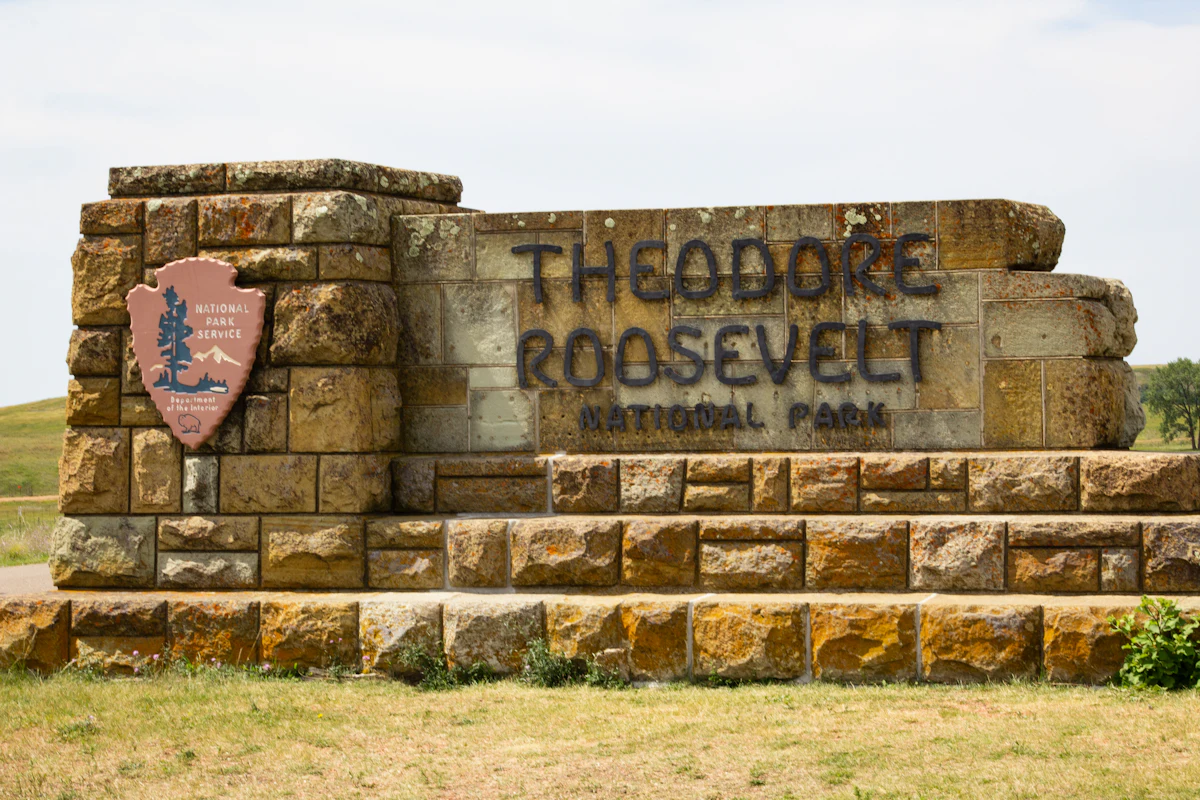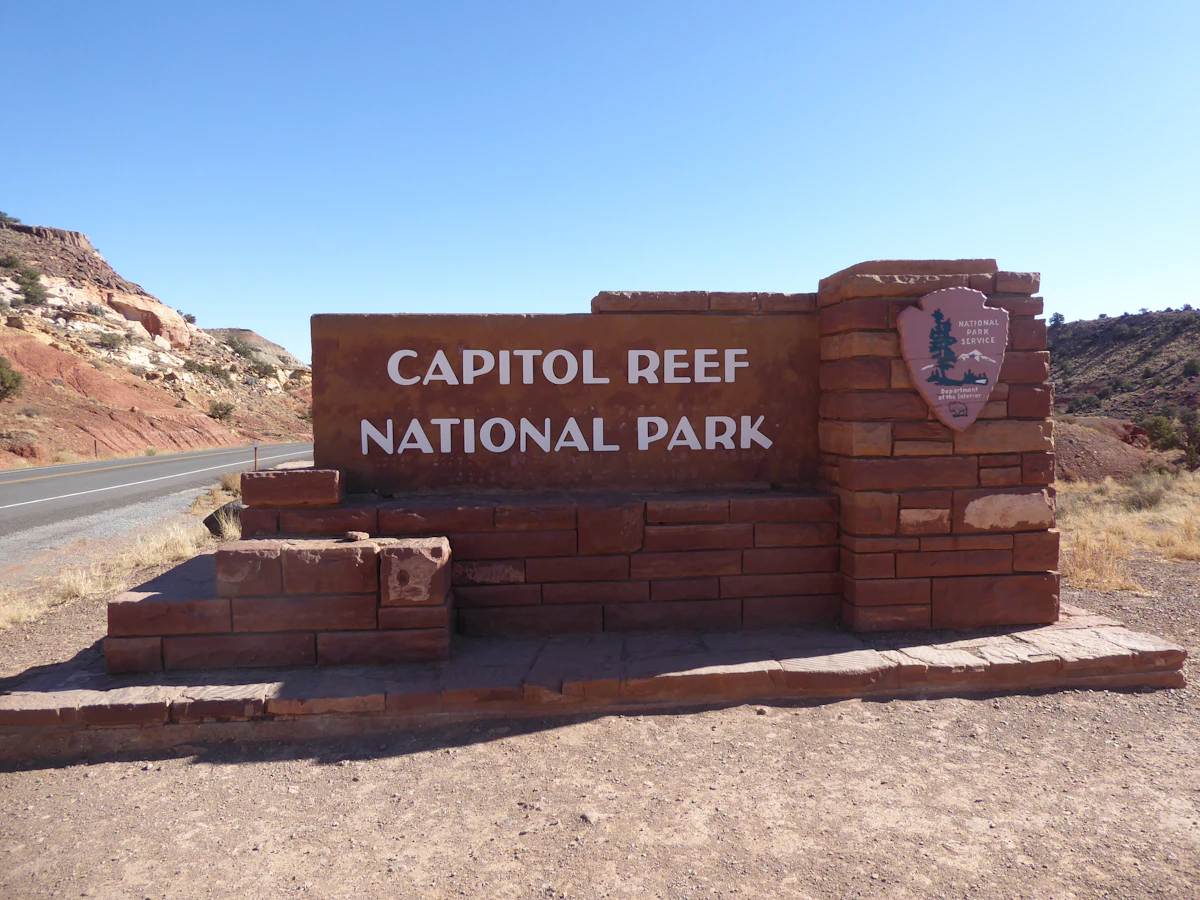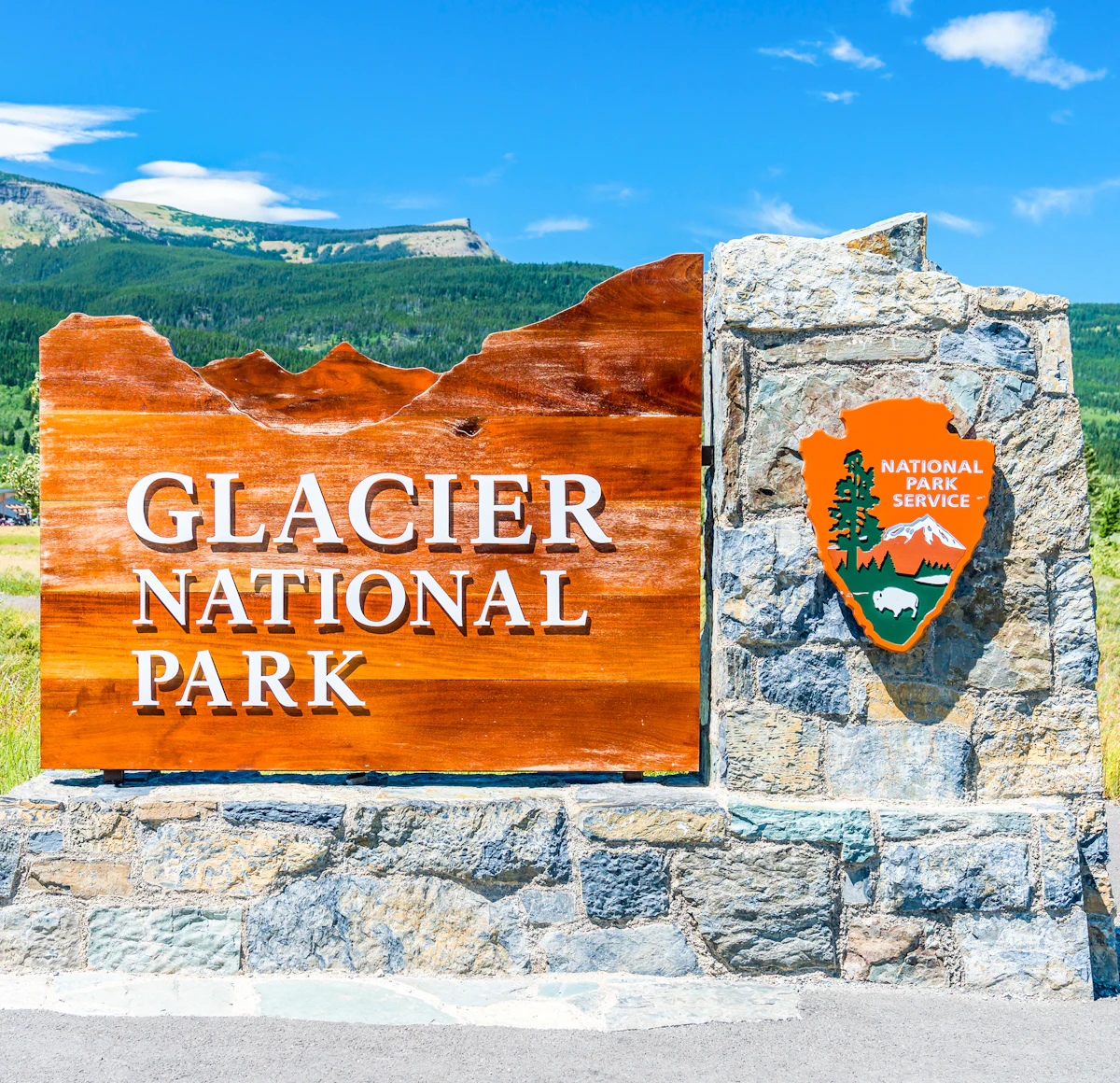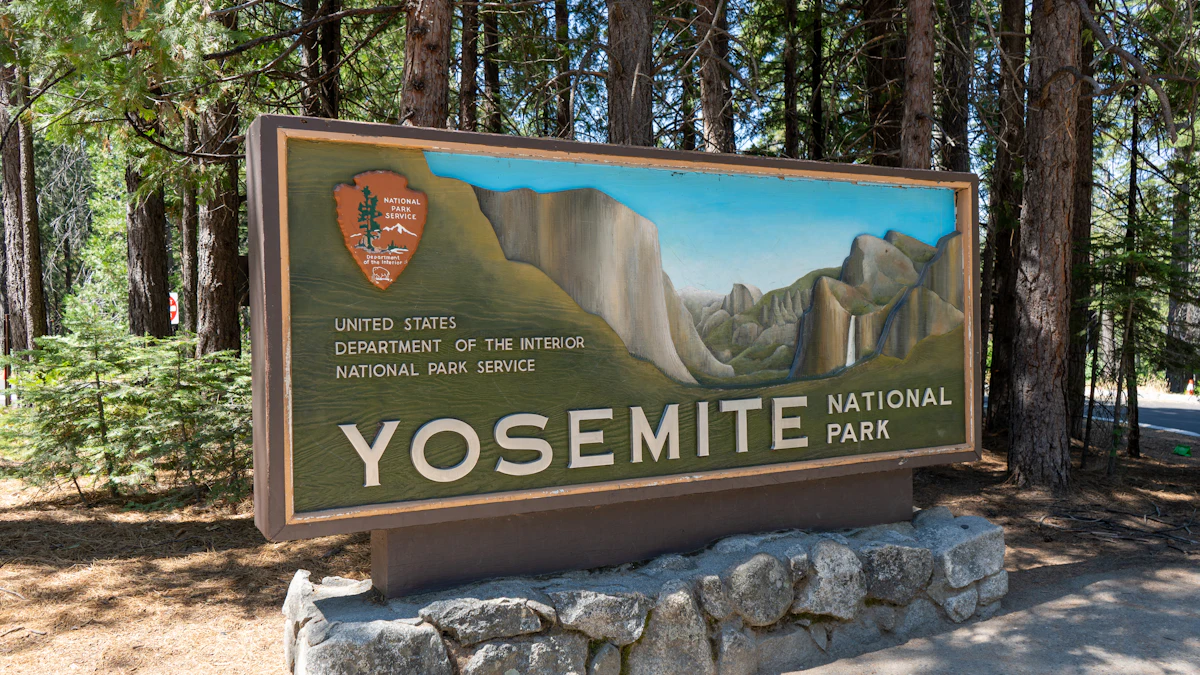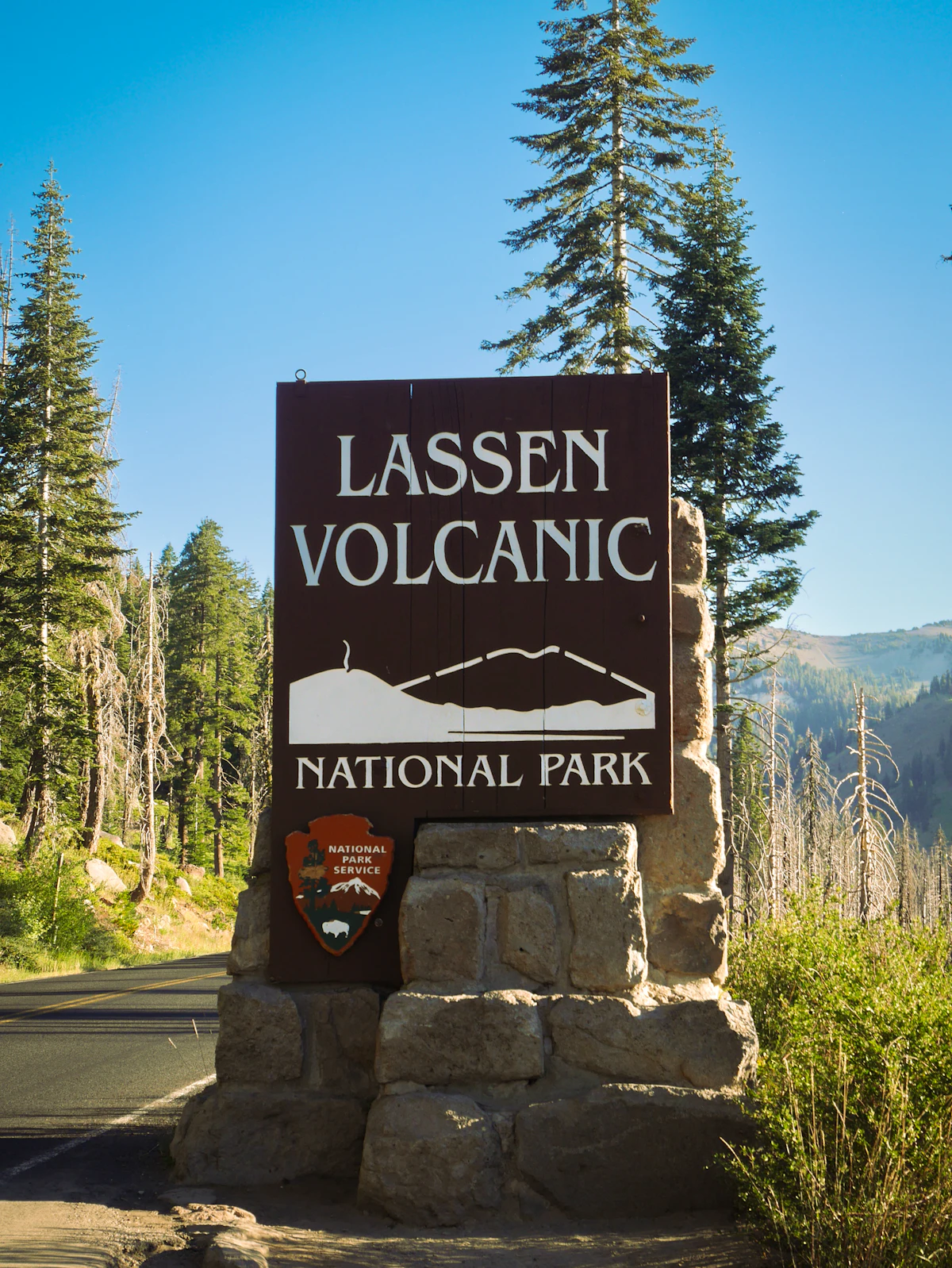
ที่ทางเข้าอุทยานแห่งชาติในอเมริกา ก่อนจะได้เห็นภูเขาหรือผืนป่า สิ่งแรกที่รถทุกคันขับผ่านคือป้ายหินหรือไม้สีน้ำตาลเข้ม บนนั้นมีชื่ออุทยานเป็นตัวอักษรหนาหนัก ปลายเส้นแต่ละขีดมีเชิงเล็กๆ โค้งรับกับเส้นตั้งอย่างพอดี หลายคนขับผ่านมันนับครั้งไม่ถ้วนโดยไม่เคยรู้ว่าตัวอักษรนั้นมีชื่อ มันคือ Clarendon
ฟอนต์ Clarendon ไม่ได้ถือกำเนิดมาเพื่อธรรมชาติหรือผืนป่าเลย มันเกิดกลางเมืองลอนดอนในปี 1845 ห่างจากอุทยานอเมริกาทั้งในแง่เวลาและสถานที่ คนออกแบบคือ Robert Besley แห่งโรงหล่อตัวพิมพ์ Fann Street Foundry
ชื่อ Clarendon มาจากสำนักพิมพ์ Clarendon Press แห่งออกซ์ฟอร์ด สิ่งที่ทำให้มันถูกจดจำในประวัติศาสตร์ตัวพิมพ์คือ Besley จดทะเบียนแบบตัวอักษรนี้ภายใต้กฎหมาย Ornamental Designs Act ทำให้ Clarendon กลายเป็นฟอนต์ตัวแรกของโลกที่ถูกจดทะเบียนคุ้มครอง ทว่าการคุ้มครองอยู่ได้เพียงสามปี พอหมดอายุ โรงหล่ออื่นก็แห่กันลอกแบบไปทันที
ป้ายทางเข้า Glacier National Park ตัวอักษร Clarendon บนแผ่นไม้
ในแง่รูปทรง Clarendon เป็นสแลบเซอริฟ คือมีเชิงตัวอักษรหนาเป็นแท่ง แต่ Besley ทำให้มันนุ่มลงด้วยการใส่เชิงโค้งตรงมุมที่เส้นตั้งบรรจบกับเชิง น้ำหนักของมันอยู่กึ่งกลางระหว่างตัวพิมพ์อียิปเชียนที่หนาทึบกับโรมันที่บางเบา เดิมทีมันถูกออกแบบมาเพื่อเป็นตัวเน้น วางคู่กับเนื้อความปกติในพจนานุกรมหรือหนังสือ เพื่อให้คำสำคัญเด่นขึ้นมาโดยไม่ต้องใช้ฟอนต์อื่น
ป้าย Yosemite National Park แกะสลักด้วยฟอนต์ Clarendon
ไม่นานหลังเกิดขึ้น Clarendon ก็ข้ามมหาสมุทรไปอเมริกา ช่วงทศวรรษ 1850 โรงงานเริ่มผลิตมันเป็นตัวพิมพ์ไม้ขนาดใหญ่ มันกลายเป็นเสียงของสิ่งพิมพ์อเมริกันที่ต้องการความหนักแน่น พาดหัวข่าวหนังสือพิมพ์ โปสเตอร์โฆษณา และโปสเตอร์ประกาศจับคนร้ายยุคตะวันตก ล้วนใช้ตัวอักษรหนาแบบนี้ในการตะโกนข้อความออกมา
ป้าย Capitol Reef National Park ตัวอักษร Clarendon สีขาวบนหินแดง
หลายสิบปีต่อมา Clarendon เดินทางมาถึงงานที่ทำให้มันเป็นที่จดจำที่สุดในสายตาคนทั่วไป นั่นคือป้ายของ National Park Service ระบบป้ายสีน้ำตาลที่กระจายอยู่ทั่วอุทยานเลือกใช้ Clarendon เป็นตัวอักษรหลัก เพราะมันให้ความรู้สึกแข็งแรงทนทานแต่ยังอบอุ่นเป็นมิตร อ่านง่ายแม้มองจากรถที่กำลังแล่น เชิงหนาๆ ของมันยังคงคมชัดแม้ถูกแกะสลักลงบนไม้หรือหิน
ป้าย Lassen Volcanic National Park ฟอนต์ Clarendon บนแท่นหิน
มีบางอย่างชวนคิดในเส้นทางของตัวอักษรชุดนี้ ฟอนต์ที่ถูกสร้างมาเพื่อเน้นคำในหนังสือ กลับลงเอยด้วยการเป็นเสียงพูดแทนผืนป่า ตัวอักษรหน้าตาเดียวกับที่เคยตะโกนคำว่า WANTED บนโปสเตอร์ ทุกวันนี้กลับทำหน้าที่บอกให้คนชะลอความเร็วและก้าวเข้าหาความเงียบ เช่นเดียวกับฟอนต์ที่ถูกออกแบบมาเพื่องานป้ายโดยเฉพาะ Clarendon พิสูจน์ว่าตัวอักษรไม่ได้แค่บรรจุข้อความ แต่กำหนดน้ำเสียงของสถานที่ไปด้วย
ป้ายหิน Theodore Roosevelt National Park ตัวอักษร Clarendon
ครั้งหน้าที่ยืนอยู่หน้าป้ายทางเข้าอุทยาน หรือแม้แต่เห็นป้ายเก่าๆ ที่ไหนสักแห่ง ลองสังเกตเชิงโค้งเล็กๆ ตรงปลายเส้นดู บางทีป้ายอาจเริ่มพูดกับเราก่อนที่ภูเขาจะได้พูดเสียอีก